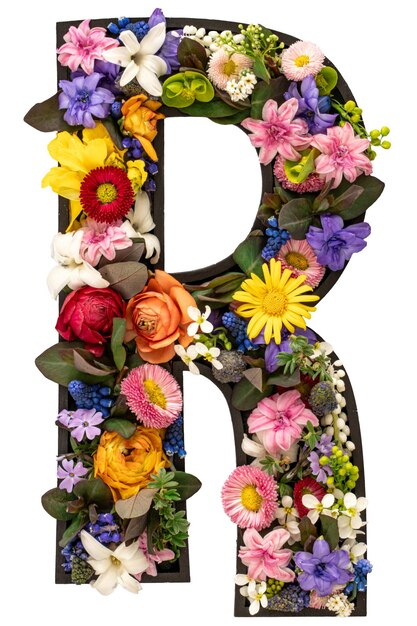
L'alphabet Png R dans le style floral isolé sur un fond transparent pour des conceptions inspirées de la nature, des marques élégantes ou des applications de typographie saisonnière